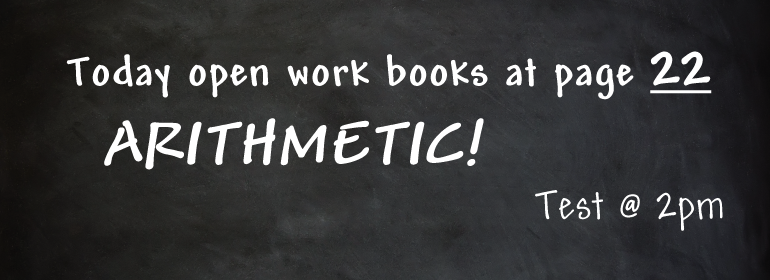
Andy™
Andy™,这款字体结构工整、笔画清晰,兼顾美观与易读性,适用于标题、正文、海报、包装、LOGO 等多种场景。字形优雅稳定,风格百搭耐看,适配日常排版与创意设计,让文字呈现更舒适、更具质感。Andy™一笔一画,皆是细节,以均衡的比例、流畅的线条打造舒适视觉体验,字形端正大气,风格简约现代。无论是商业设计、品牌宣传还是日常排版,都能轻松驾驭,让文字更有格调与力量。Andy™字体下载。
字体品牌: Monotype 设计师:Matteson,Steve 字体分类:手写风格字体 字体属性:外文 字符集:Unicode 发布时间: 2018